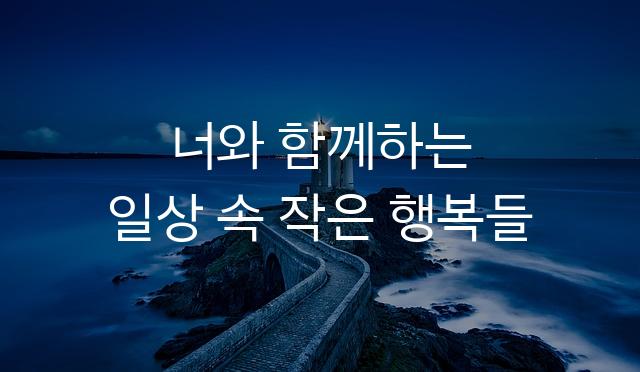
팔칠엠엠 일상 기울임은 현대적 감각이 묻어나는 기본 고딕 스타일의 이탤릭 폰트입니다. 일상적인 디자인에도 유니크함을 더해줄 수 있는 폰트입니다.
팔칠엠엠 일상 기울임은(는)
기본 고딕, 기울임, 감성적인, 부드러움 계열의 생김새를 가지고 있으며
포스터, 소셜 미디어, 일기/편지 등에서 자주 활용되며, 효과적인 메시지 전달에 적합합니다.
이 폰트는 라이프스타일, 문화/예술, 유아/가족 분야에 잘 어울리며,
친근한, 편안한, 단순한 느낌을 담고 있는 것이 특징입니다.
이 폰트와 유사한 폰트로는 나눔고딕, 맑은고딕, 스포카한산스 등이 있어요. 함께 비교해 보시면 좋습니다!